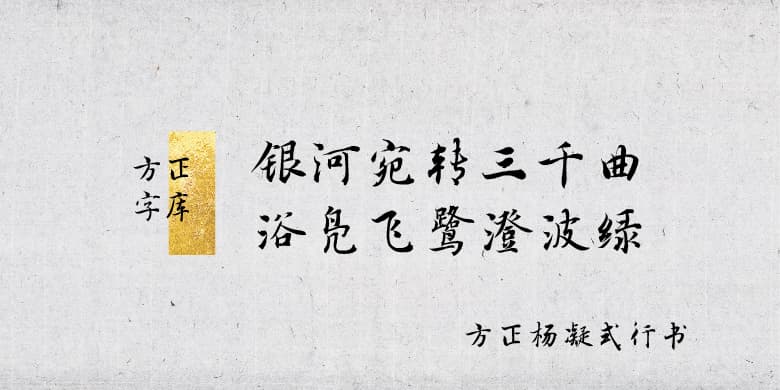
方正杨凝式行书
关于杨凝式:
杨凝式(873~954年),字景度,号虚白,华州华阴(今陕西华阴)人。唐末五代时期宰相、书法家。在书法历史上历来被视为承唐启宋的重要人物。“宋四家”都深受其影响。代表作品有《韭花帖》、《卢鸿草堂十志图跋》、《神仙起居法》。
字体特征:
以杨凝式《韭花帖》为临创开发依据,字体点画生动,结构端稳,风神简静;结体妍丽,整体端庄而温雅;笔法巧妙,用笔一丝不苟却毫无古板呆滞之感,文人之气十足。
临创者:周易